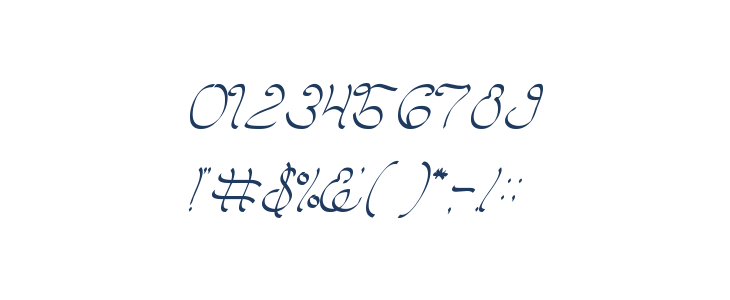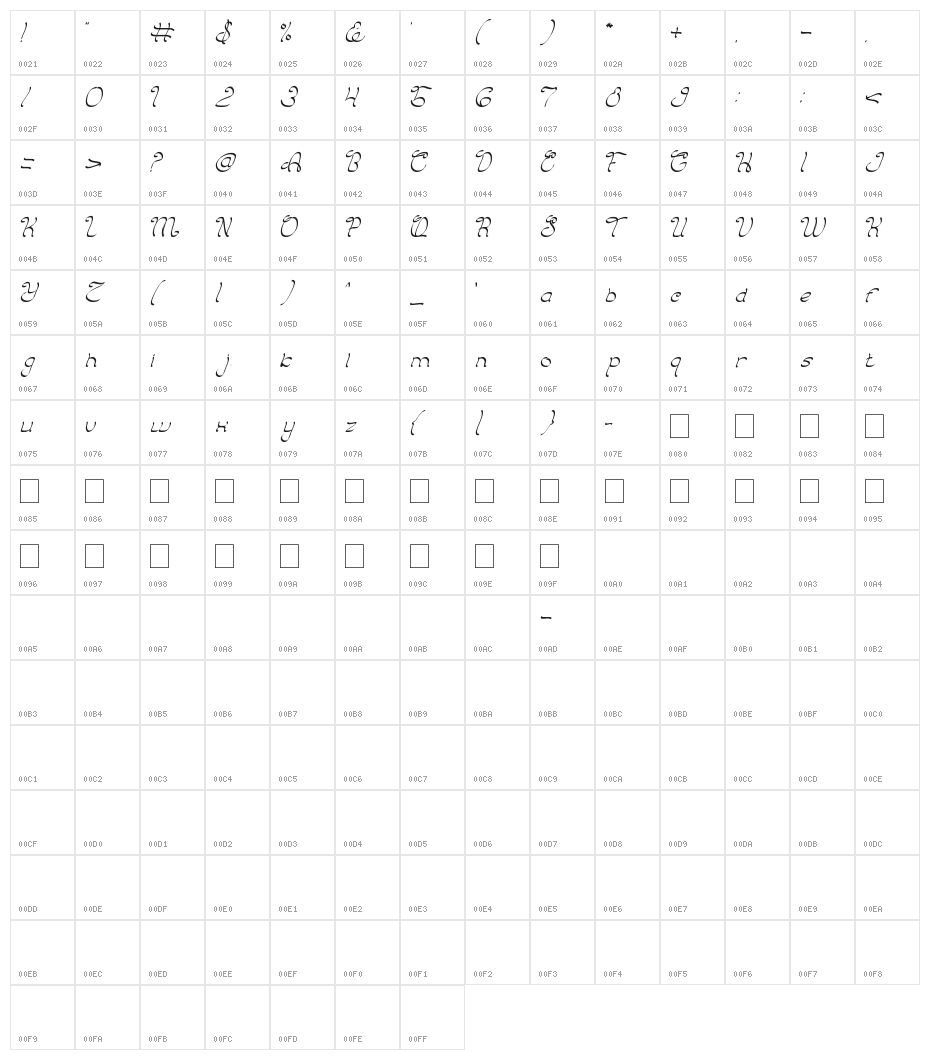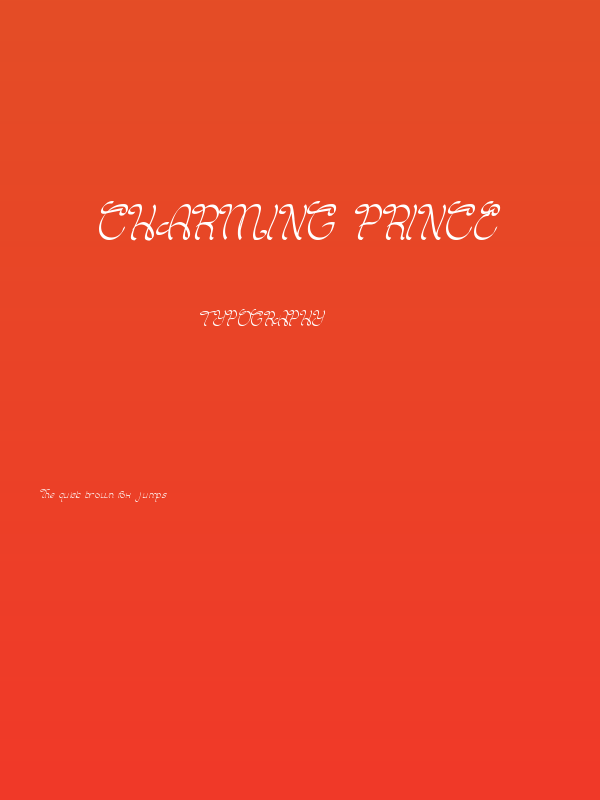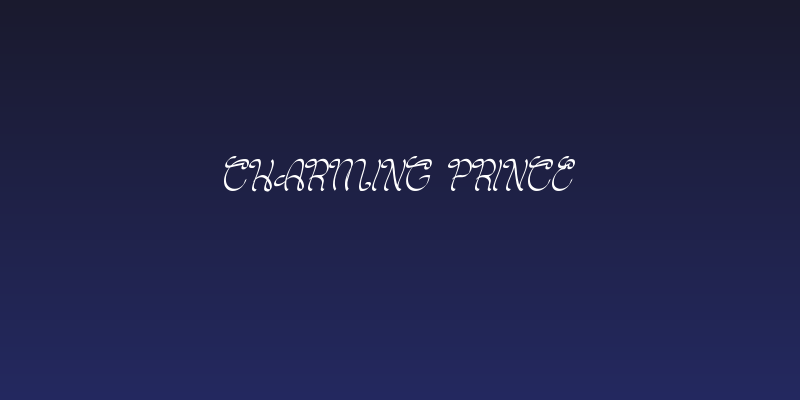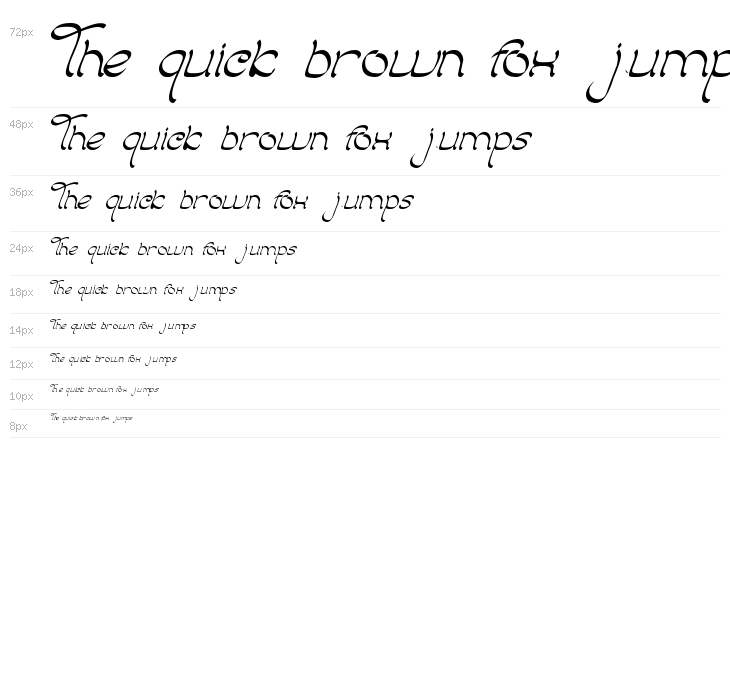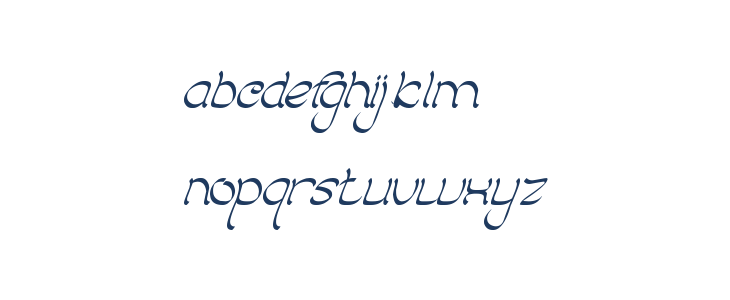
Charming Prince Font
| Stile generale | Romantic, Elegant |
| Caso d'uso | Logos, Invitations, Decorative text |
| Progetti proposti | Ideal for wedding invitations, elegant branding, romantic greeting cards, and upscale packaging designs. |